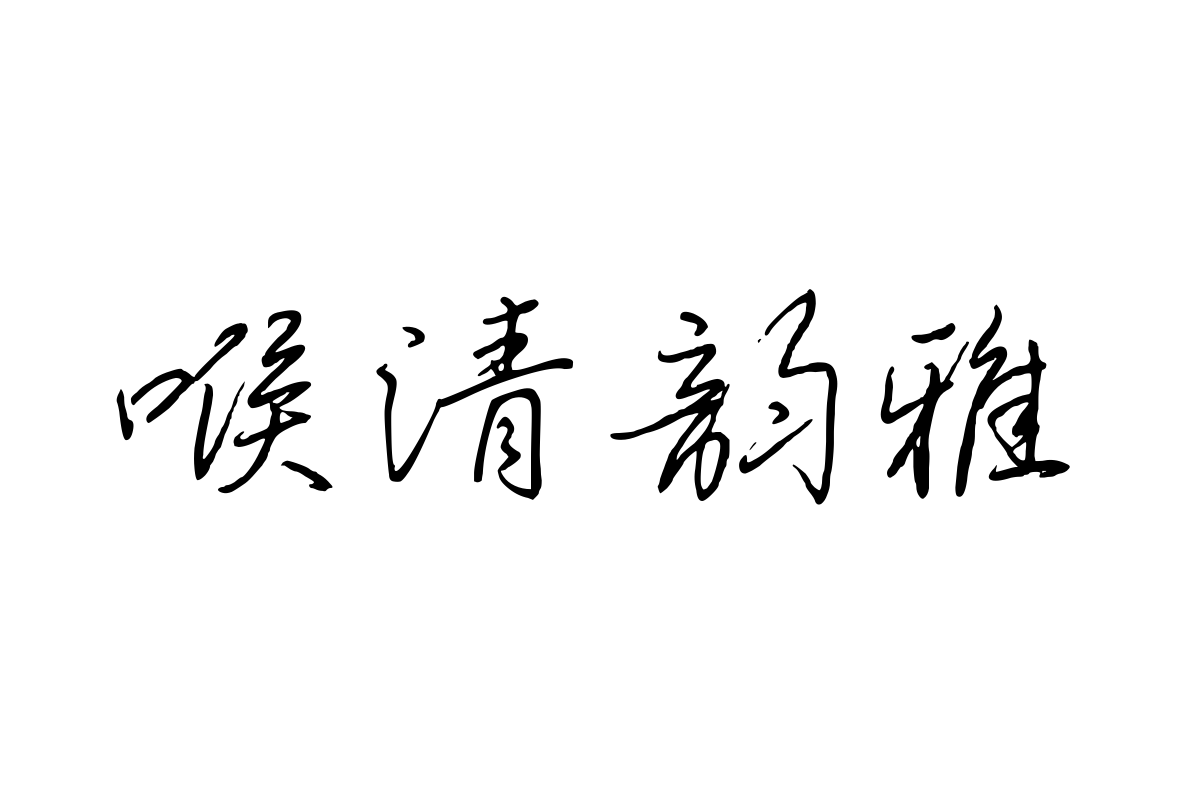
文道硬笔行书体是一种独特的书法字体,它结合了硬笔和行书的特点。这种字体的笔画流畅,结构紧凑,给人一种简洁明快的感觉。它的线条粗细不一,既有行书的舒展,又有硬笔的刚劲,使得整体效果既具有书法的韵味,又不失现代感。
文道硬笔行书体的特点是:笔画流畅,结构紧凑,线条粗细不一,既有行书的舒展,又有硬笔的刚劲。这种字体适合用于各种场合,如广告、宣传、签名等。